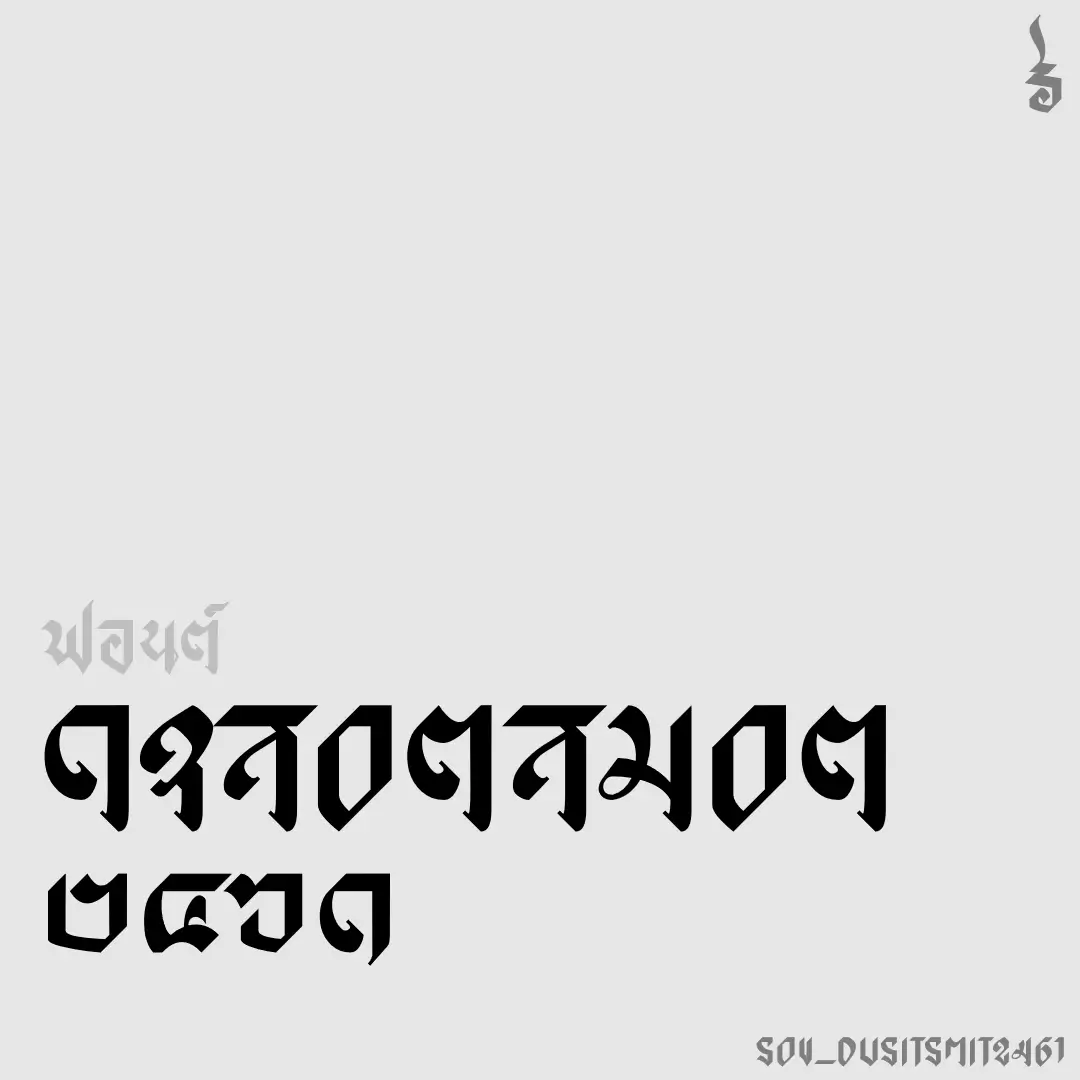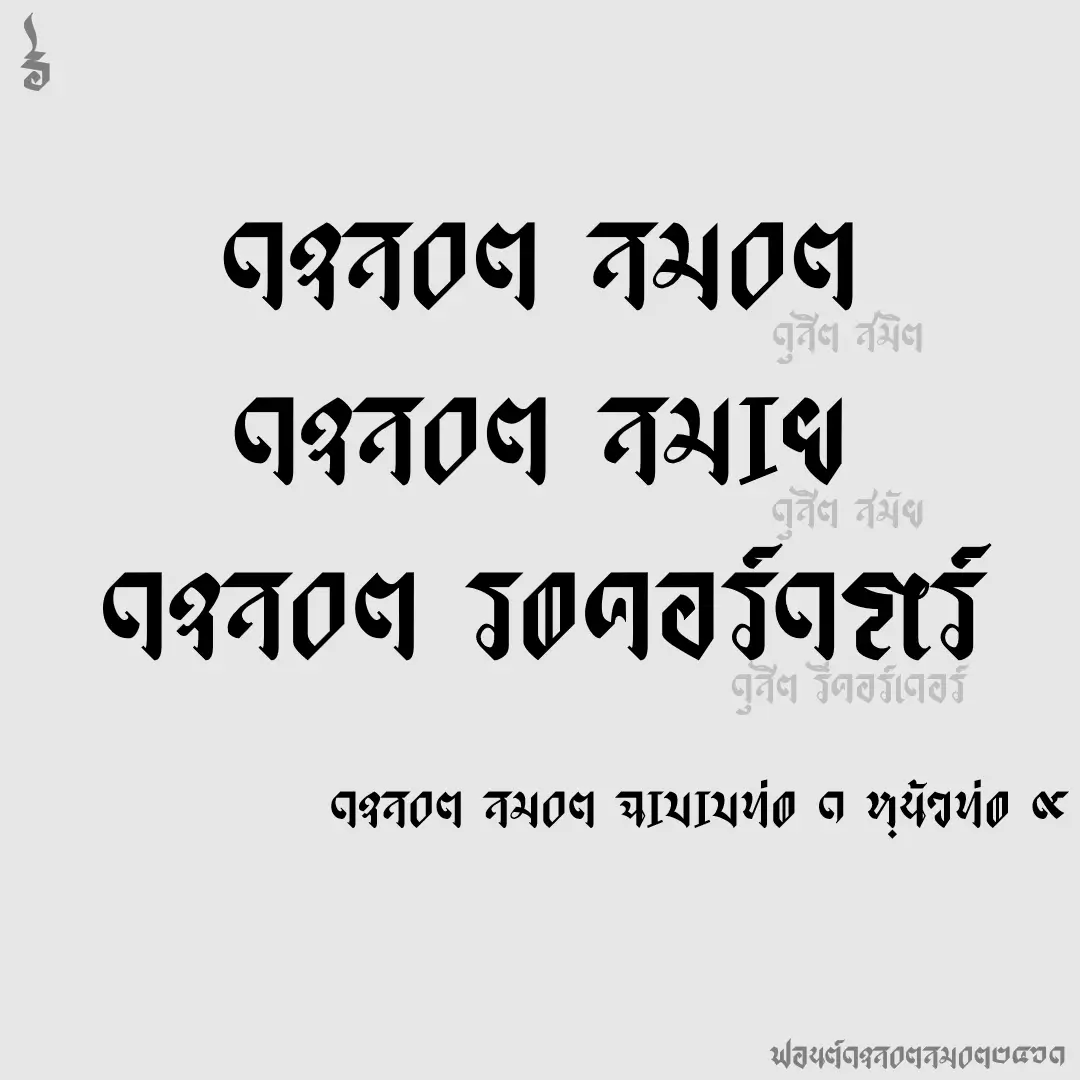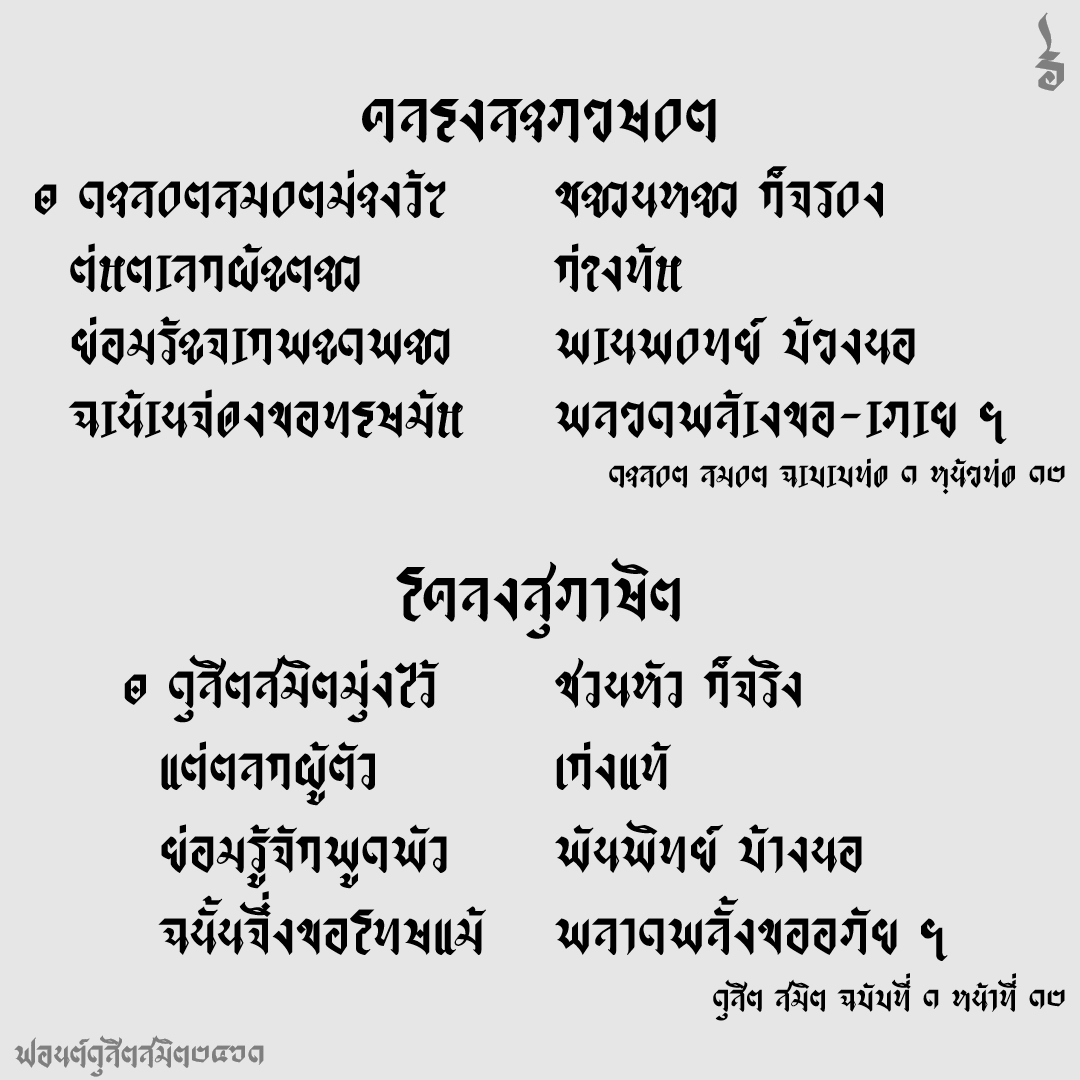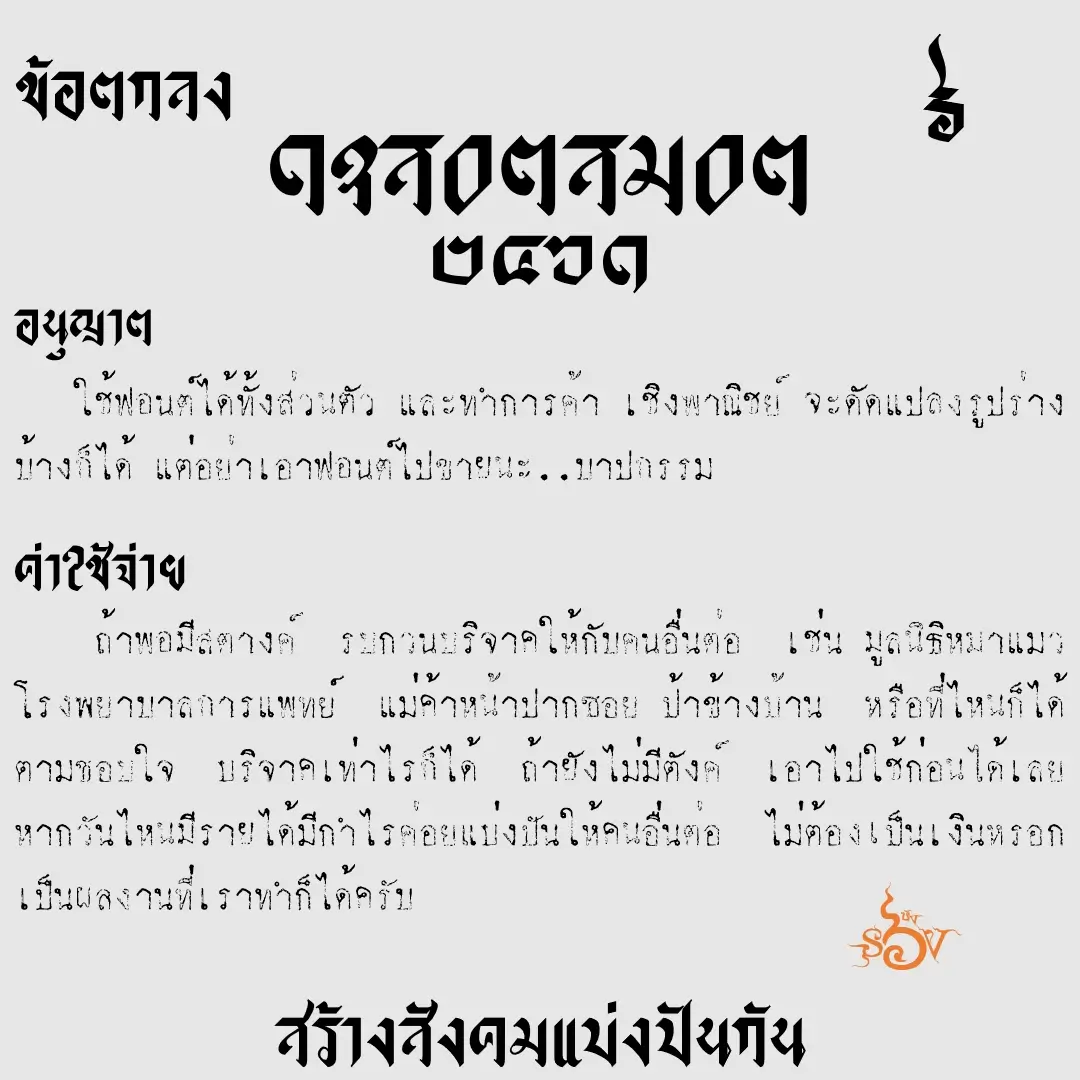
ฟอนต์ดุสิตสมิต๒๔๖๑ – ต้นแบบจากหัวหนังสือพิมพ์ “ดุสิต สมิต” เมื่อปีพ.ศ. ๒๔๖๑ เขียนด้วยอักขรวิธีใหม่สมัย ร.6
เบื้องหลังการออกแบบ : ฟอนต์ ดุสิตสมิต๒๔๖๑
ดุสิตสมิต๒๔๖๑ (SOV_DusitSmit2461)